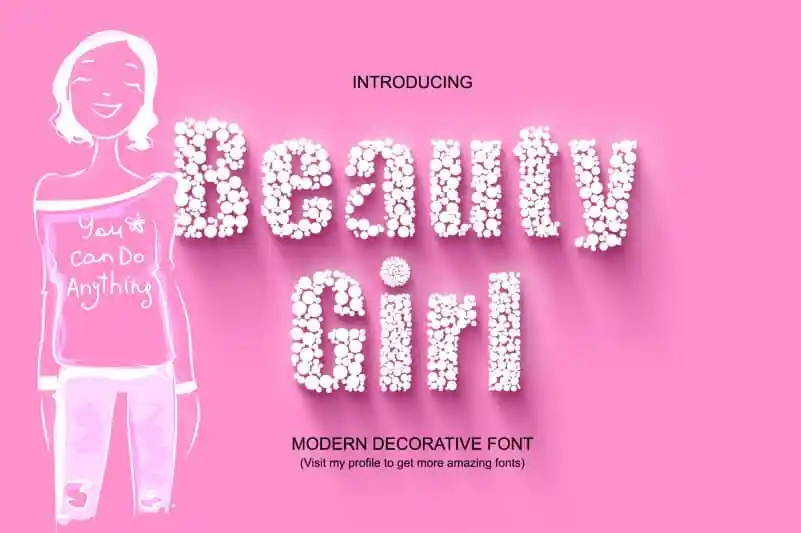
Beauty Girl Font – Download Grátis
A ‘Beauty Girl Font’ é uma elegante e única fonte decorative que irá enriquecer qualquer projeto visual com seu charme romântico. Seja para cartas apaixonadas, convites de casamento ou até mesmo um design pessoal favorito, essa fonte transformará suas ideias em algo inconfundivelmente atraente e único. Ela é perfeita para quem busca uma personalidade distintiva que enriqueça qualquer projeto gráfico. Com o ‘Beauty Girl Font’, sua arte ganha vida com uma delicadeza e sofisticação, oferecendo um toque especial de amor em cada detalhe.